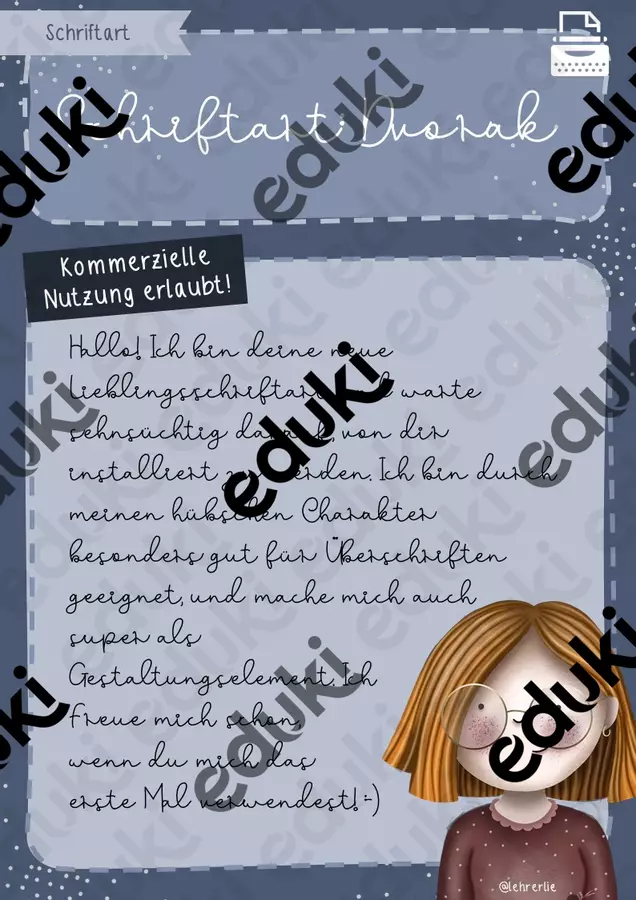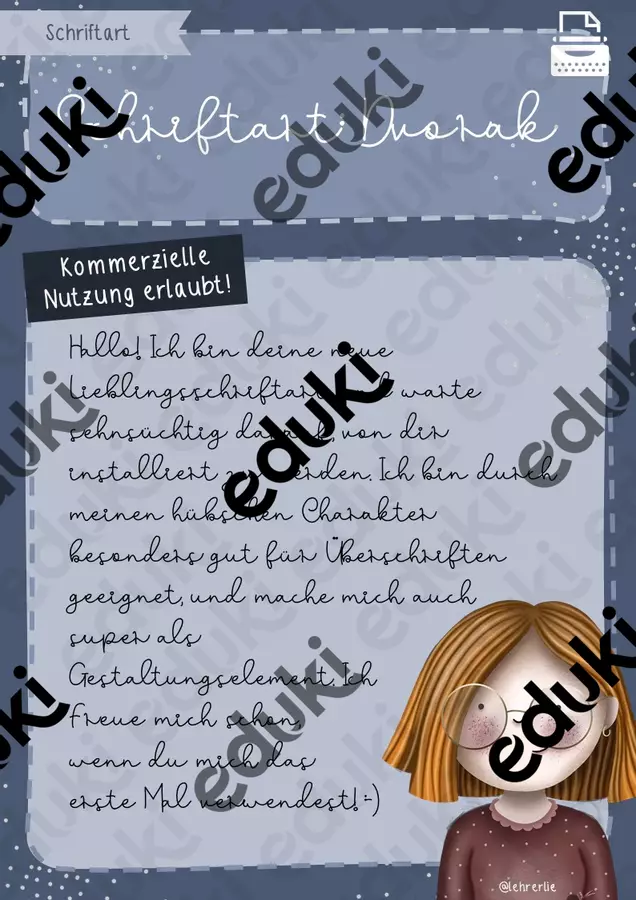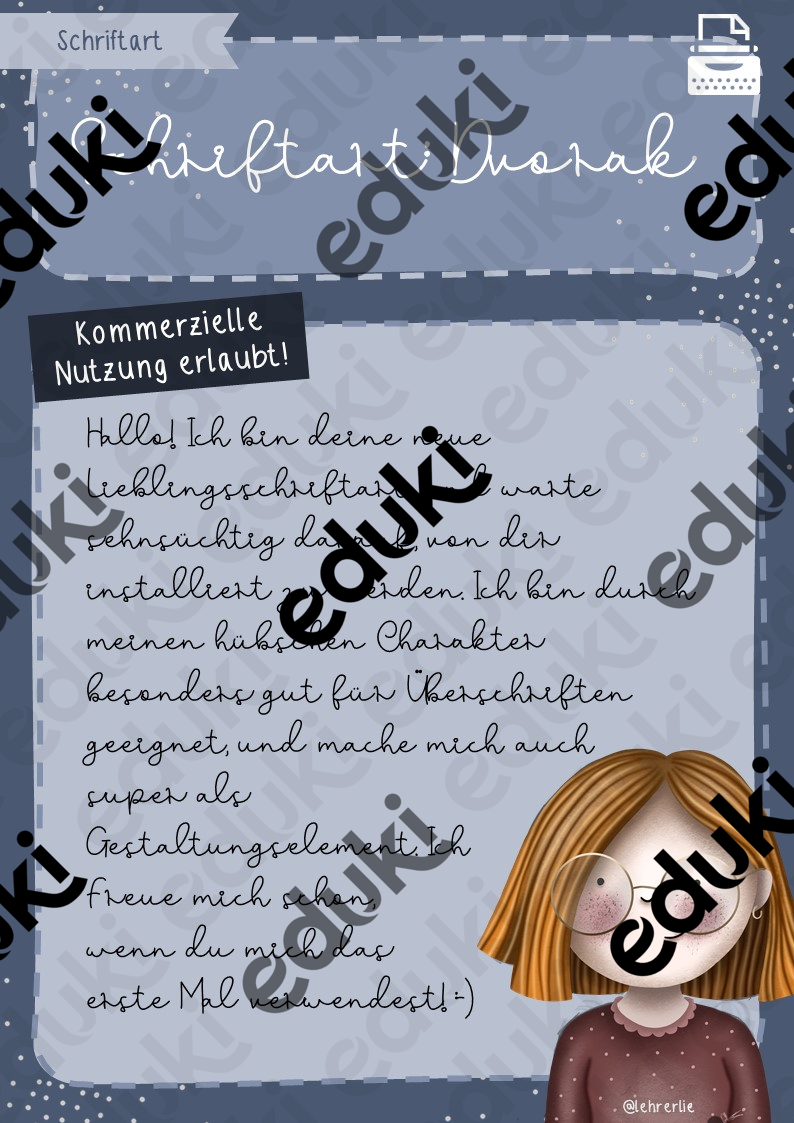
selbst erstellte Schriftarten - Schriftart: Dvorak by Pinselkomponistin - Deckblatt
Weiter geht es im Zuge der Komponisten-Schriftarten! Mit "Dvorak" bekommt ihr mal wieder eine Schriftart, die sich besonders toll für Überschriften oder zum ästhetischen Gestalten eignet.
Schriftart: Dvorak by Pinselkomponistin